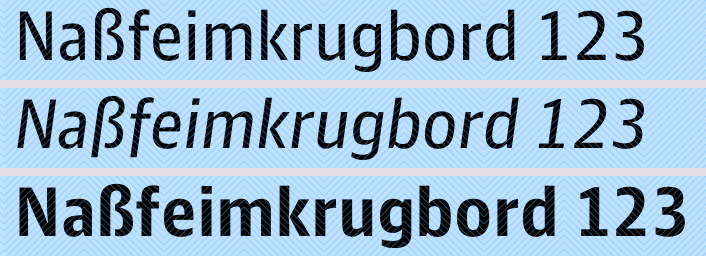
Schriftart für Tabellensatz
Ich suche eine Schriftart, die für den Tabellensatz passt. Sie sollte auch bei kleineren Schriftgraden (7-8 Punkt) noch gut lesbar sein. Ins Auge gefasst habe ich schon mal die Myriad Pro. Gibt es noch andere gute Schriften, die für diesen Einsatzzweck geeignet sind? Bitte um Vorschläge, danke.
Von Fontshop speziell für den Einsatz in Excel beworben:
Schmal laufend und bildschirmoptimiert ... klingt überzeugend, probiert hab ich's nicht.
Aber: Meinst du Tabellensatz generell (in einem Grafikprogramm) oder technisch (in einem Kalkulationsprogramm)?
ich bin von der oben genannten axel begeistert. sie erfüllt ihren zweck am bildschirm hervorragend und auch gedruckt ist sie gut lesbar.
geht es um komplexere tabellen, fremdsprachiges etc. dann nehme ich die hypatia. für mich haben sich in tabellen sans serife bewährt, da die tabellenstruktur schon ausreichend das auge führt.
Danke für die Vorschläge. Es geht hauptsächlich um Tabellensatz in einem Kalkulationsprogramm (OOo 3 Calc) für Abrechnungen, EÜR und Auflistungen.
Die FF Fago Offc wäre auch dafür geeignet …